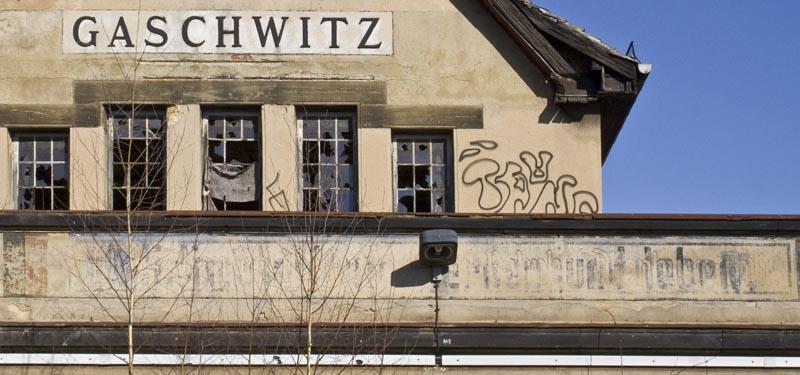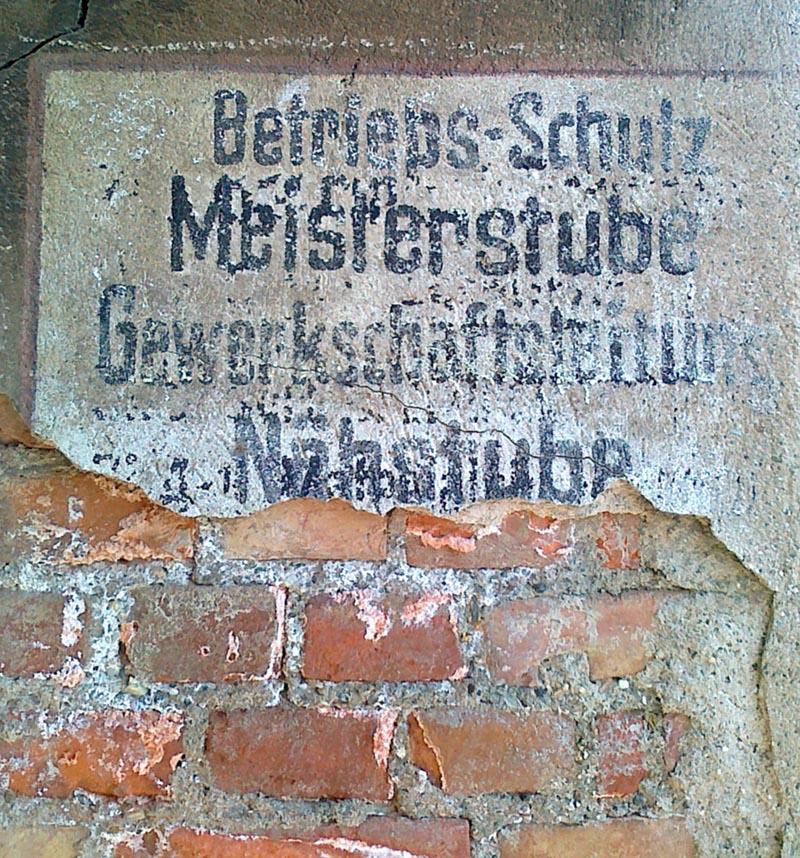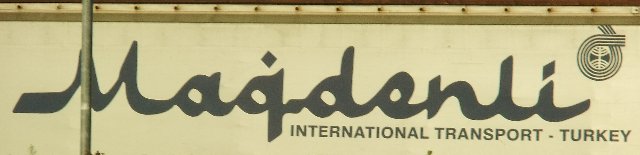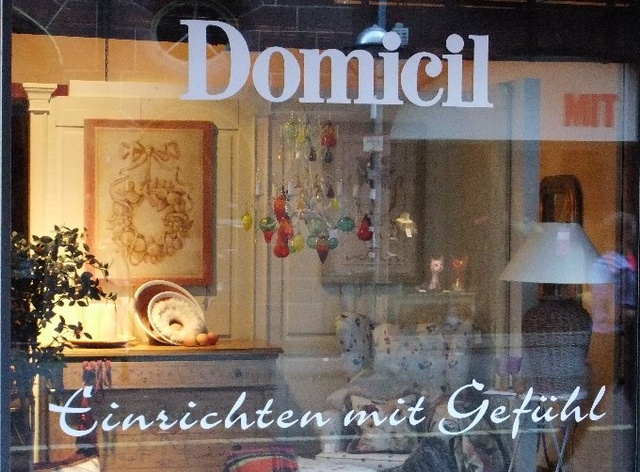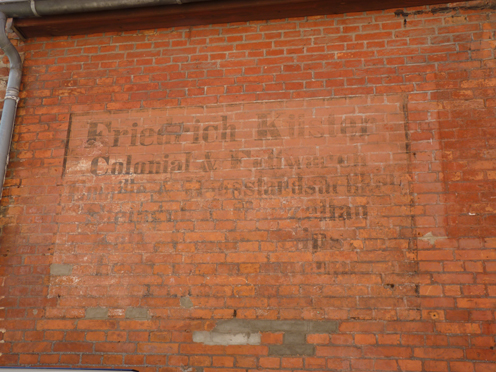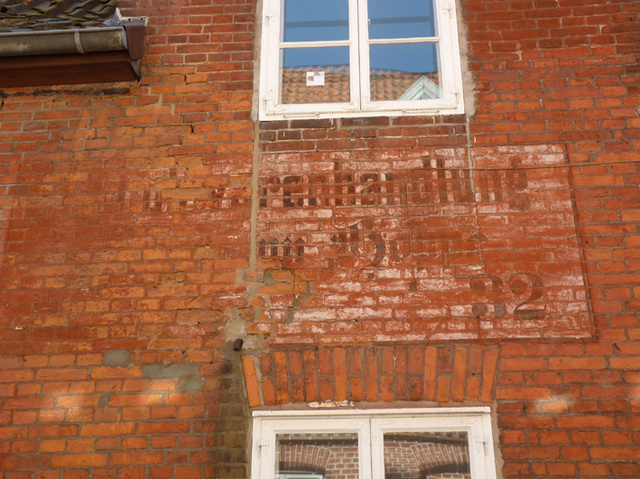
Aus der Serie der kleinen und großen Missverständnisse des kleinen großen Muecks ...
Hier ein Photo beim Halt des IC in Walldorf-Wiesloch, in dem ich kürzlich saß.
Ich dachte nicht nur an ein seltenes Fundstück eines ohne u seltenen q (aber in der Sprachecke schon eher vorkömmlich), sondern an eine ganz, ganz seltene Rarität eines q mit Akzent!
Ganz real ist's eher ein banales Fundstück ...
Auflösung: ein g mit Breve Wer hat's noch "richtig" erkannt?
Liegt es am Font? Whatthefont hat den invertierten und zerlegten Schriftzug keiner Schrift zuordnen können, also evtl. selbst gemalt mit allen Irritationen ...
Das nächste war ein Verleser, an den ich wieder dachte, als es kürzlich wieder mal an anderer Stelle im Forum um eine [sZ][/sZ]-B-Irritation ging ...
Frei nach dem Motto:
Einsichten mit Gefühl sind der erste Schritt zur emotional-orthographischen Besserung der Lesekompentenz in Verbindung mit dem die Wortbedeutung nahelegenden Schaufensterinhalt ... ;-)
Vielleicht ist das mal ein Versal-ß im Gemischtsatz. Wäre doch mal was Neues unter den ganzen kleinen Eszett im Versalsatz …
Das wäre doch mal ein anspruchsvolles Typo-Sommer-Rätsel! ;-)
Die Herausforderung für Denkmalschützer und Restauratoren ist auch nicht ohne.
Hier etwas aus Leipzig:
in dem Genre hätte ich auch etwas - gefunden in Lüneburg
Das wäre doch mal ein anspruchsvolles Typo-Sommer-Rätsel! ;-)
Hehe – allerdings ;-)
Hier etwas aus Leipzig:
Eine bemerkenswerte Kombination!
Und aus Neuruppin:
Das einzige was ich jetzt auf Anhieb entziffern kann ist: „Bahnhof Altenburg Thür.“, beim Rest muss ich erst einmal passen.
Das einzige was ich jetzt auf Anhieb entziffern kann ist: „Bahnhof Altenburg Thür.“
Das ist schon mal eine reife Leistung, allerdings ist der Befund auch verwirrend: Wieso steht am Bahnhof Gaschwitz etwas vom (ca. 40 km entfernten) Bahnhof Altenburg?
Das könnte es sein!
Siehe auch hier und hier.
Wieso steht am Bahnhof Gaschwitz etwas vom (ca. 40 km entfernten) Bahnhof Altenburg?
War das vielleicht ein Zubringerbahnhof auf der Strecke nach Altenburg?
Das ist schon mal eine reife Leistung, allerdings ist der Befund auch verwirrend: Wieso steht am Bahnhof Gaschwitz etwas vom (ca. 40 km entfernten) Bahnhof Altenburg?
War das vielleicht ein Zubringerbahnhof auf der Strecke nach Altenburg?
Ja, Gaschwitz liegt auf der Bahnstrecke Leipzig-Hof, auf der auch Altenburg liegt.
Vielleicht gab es zwei Bahnsteige, einen in Richtung Altenburg und einen in die Gegenrichtung? Und die Richtung Altenburg war ans Gebäude geschrieben, während gegenüber ein Schild mit der Gegenrichtung stand? Ich spinne jetzt nur mal so rum …